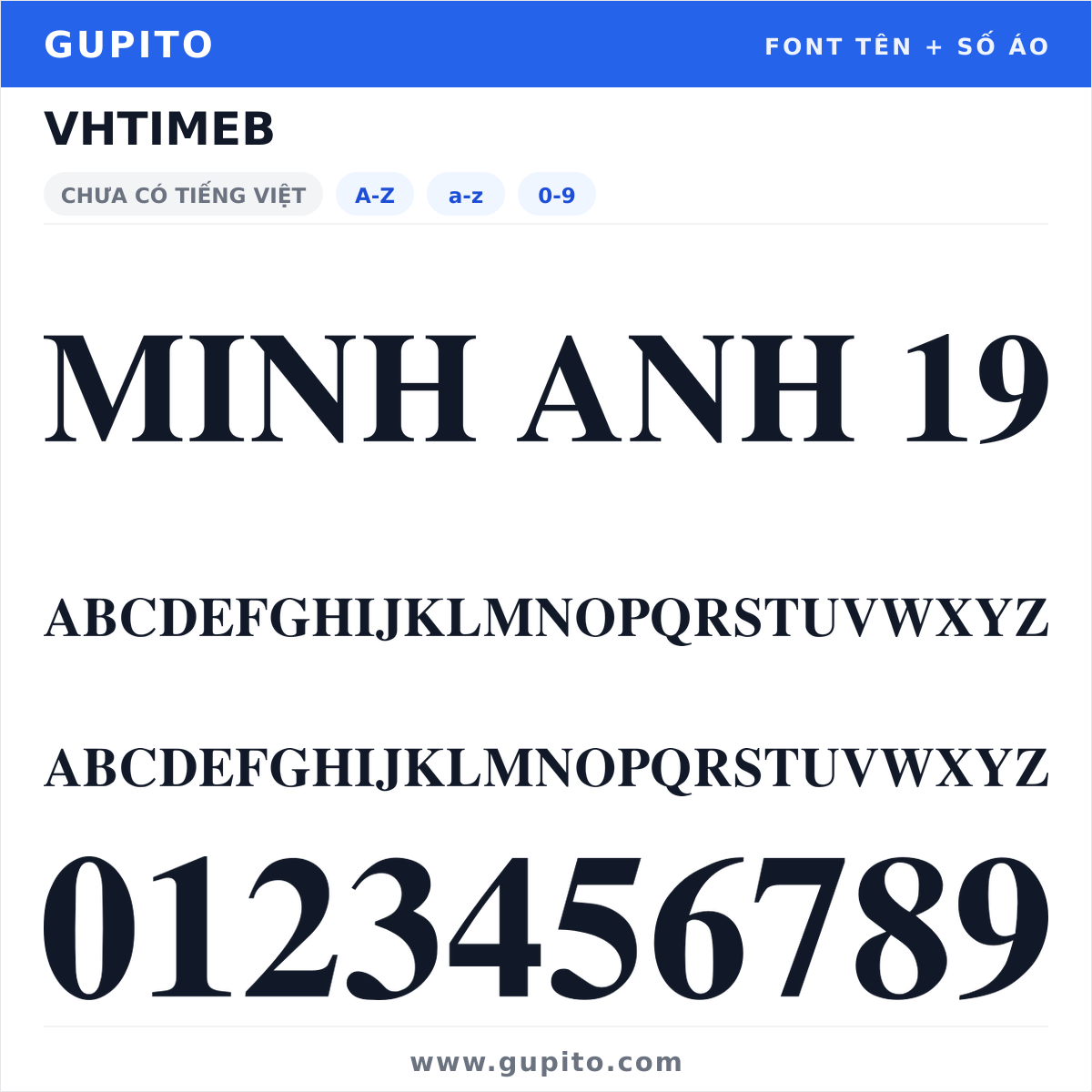
.VnTimeH Bold
.VnTimeH Bold · Font VHTIMEB in tên áo bóng đá, áo lớp, áo đội · chân serif cổ điển
Font VHTIMEB với nét chữ đậm, chân serif cổ điển, phù hợp in tên áo bóng đá, áo lớp, áo đội, quà tặng. Có bảng số 0-9. Bộ chữ .VnTimeH Bold dùng để in chuyển nhiệt lên áo đấu, áo lớp, áo nhóm và đồ thể thao theo yêu cầu. Kiểu dáng: chân serif cổ điển. Font dùng cho chữ không dấu và số áo. Có đủ bộ chữ số để in số áo. Từ khoá liên quan: font vhtimeb, font in ten ao, font in so ao, font ao bong da, font ao lop, font in chuyen nhiet, font co bang so, font chu hoa.